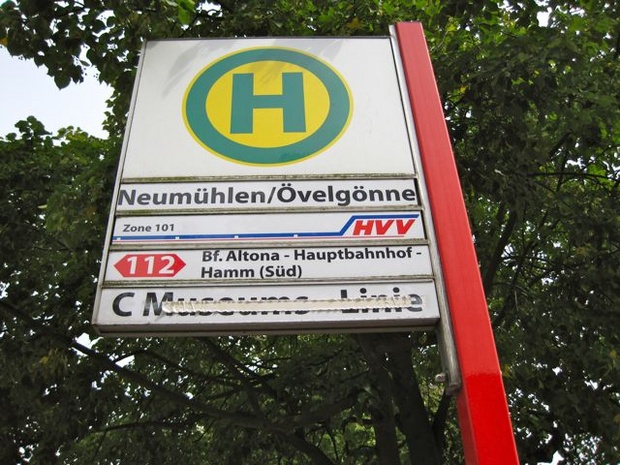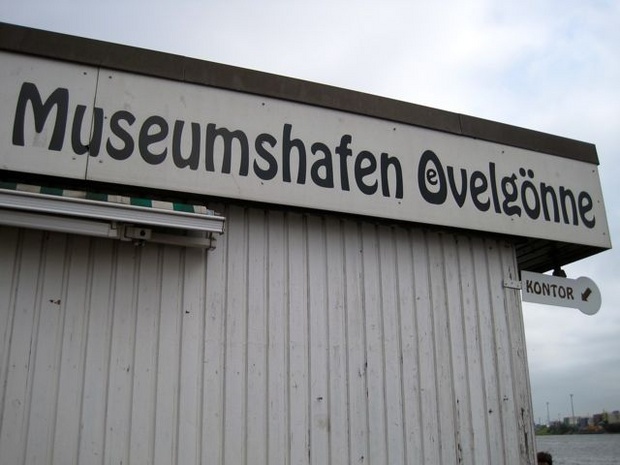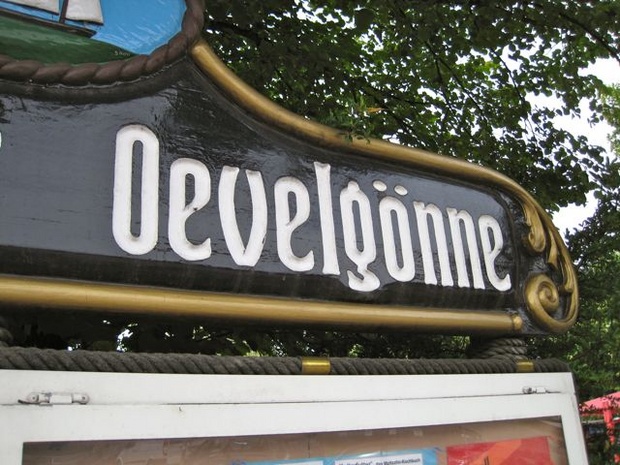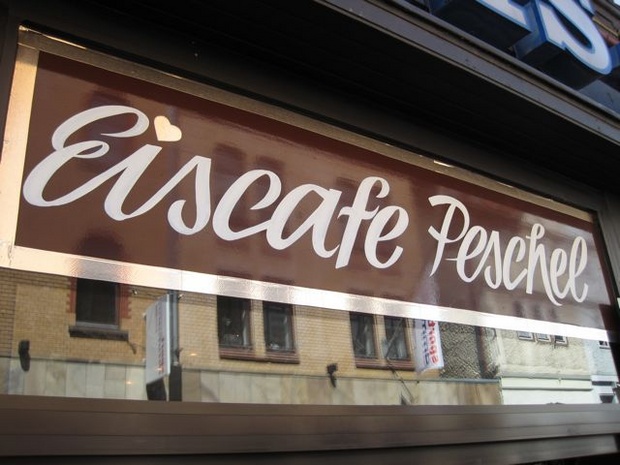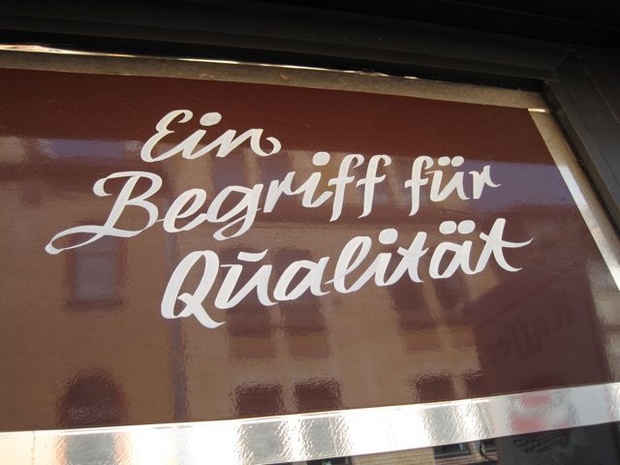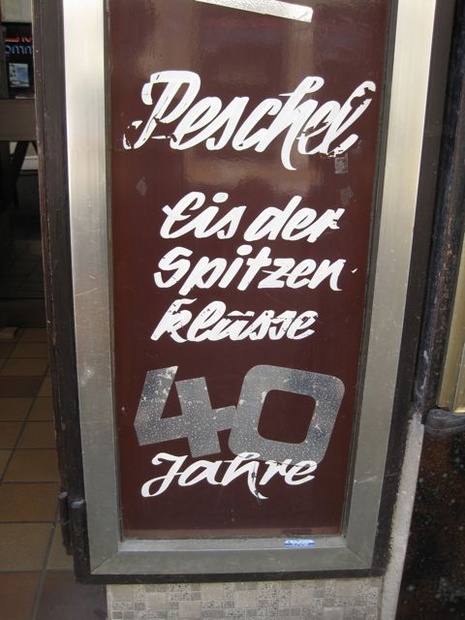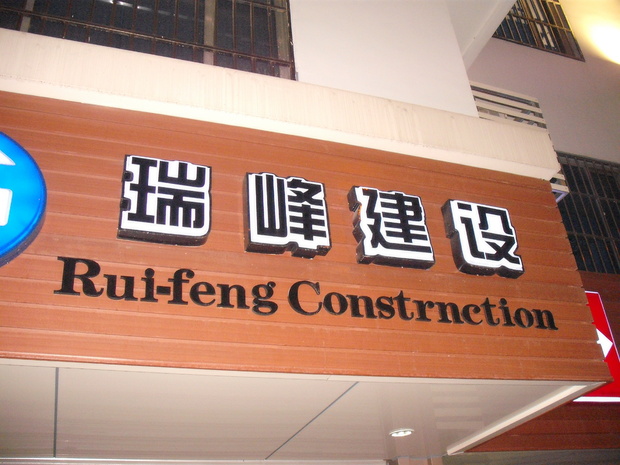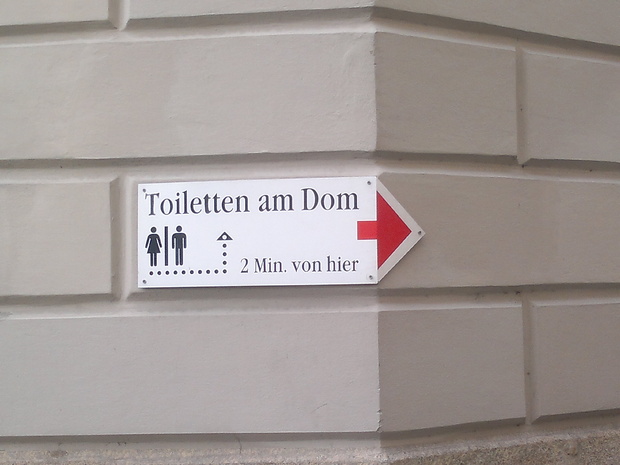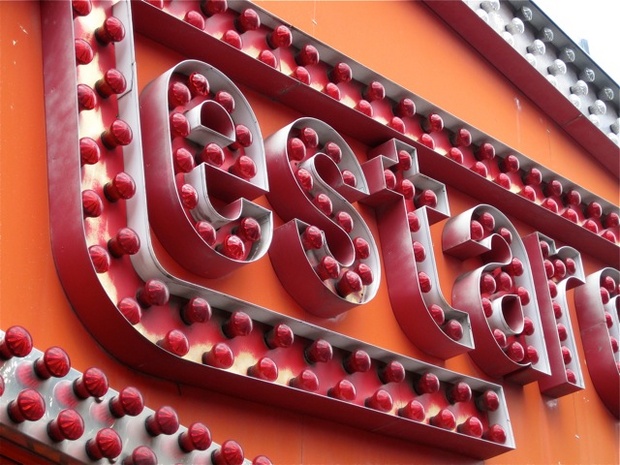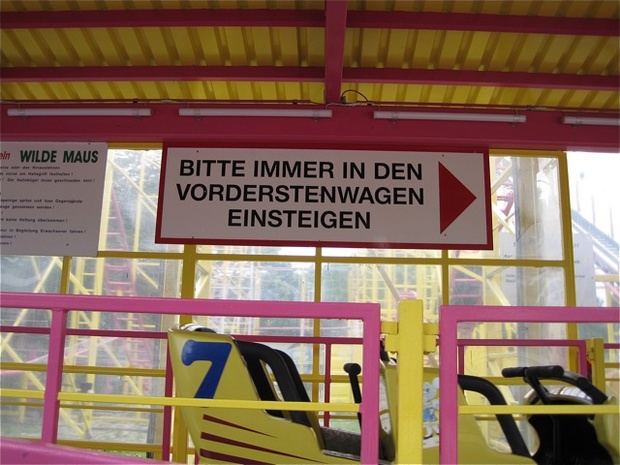
Typostreifzug durch die Stadt ...
hm, was gefällt daran nicht?
mir gefällt nicht, dass das letzte s von cyclassics unsanft durch den bildrand von einem teil seiner substanz getrennt wird.
Na es klemmt schon ein bisschen arg im Kasten … Bisschen Luft rechts und links hätten sie ruhig noch dazu kaufen können … ;-)
d’accord. Ich könnte mir aber auch vorstellen dass das s richtig angeschnitten wird, um die Dynamik nach rechts zu verdeutlichen.
… nach Absicht aussehen … ;-)
Und zwar deutlich. ;-)
auch ich bin immer wieder auf dem Streifzug durch Hamburg, dabei kann man die ein oder andere sehr interessante Entdeckung machen. :)
Da hat sich jemand wirklich Mühe gemacht. Schade nur, daß da wohl mal ein „t“ geklaut und etwas fett ergänzt wurde.
Das soll wahrscheinlich die weibliche Form verdeutlichen, die Langform wäre "Toilen und Toiletten".
Gute Idee, die zwei „t" durch Symbole zu ersetzen.
Na dir kann aber auch keiner nen n für’n u vormachen was? ;-)
Hier die Beute meines letzten Typostreifzuges, den ich ausnahmsweise mal nicht in meiner geliebten Heimatstadt unternommen habe sondern im wunderschönen Wien. :biglove: (mal sehen, wer das ß zuerst findet!)
sind euch noch mehr Stadtalphabete bekannt? Ich finde diese Idee echt spannend und würde gern wissen, ob es ähnliche Projekte gibt (in Bezug aufs Alphabet).
Doch, beim Herrn Strauß, habe ich eins gefunden :-D
Ja, das hab ich auch gesehen. Auch, dass bei "Verhaltensmassregeln" eines fehlt :-)
Wie ist denn das in Österreich überhaupt mit den ß-Regeln geregelt? Vielleicht haben die das Wilde-Maus-Schild aus der Schweiz importiert?
»Vorderstenwagen« fand ich übrigens auch eigenwillig. Schreibt man das in Österreich so?
In Österreich gelten bezüglich des ß eigentlich die gleichen Regeln wie in Deutschland, wenn ich das jetzt nicht falsch in Erinnerung habe.
Ah danke! Dann ist das »1. Wiener Ponny-Caroussel« vermutlich eine historische Schreibweise?
Sehr gefallen hat mir übrigens auch »Hundeschuranstalt«. Da weiß der arme Hund doch gleich, was die Stunde geschlagen hat. (Mit solchem Schnickschnack müsste man meinen Katzen mal kommen …;-))